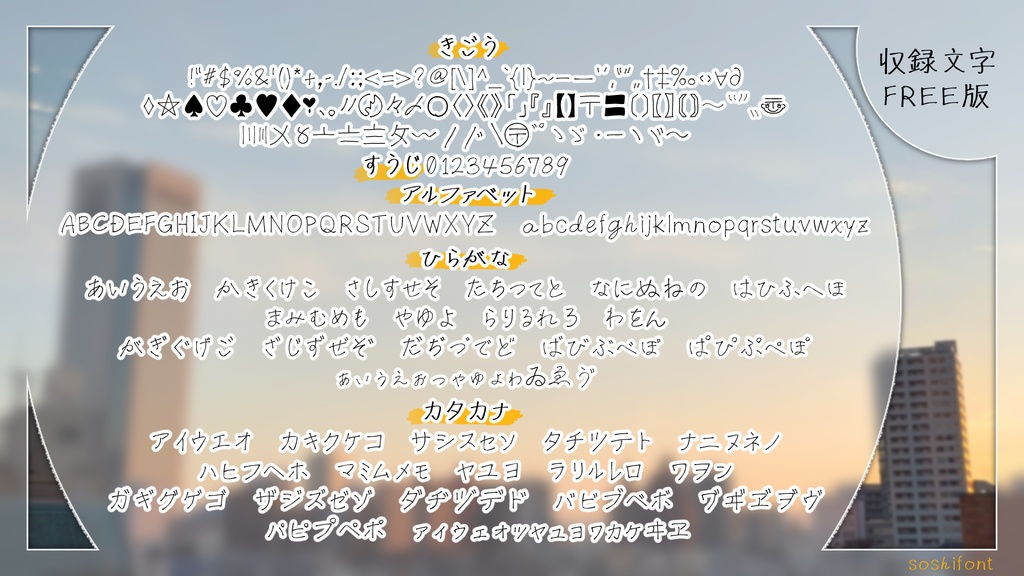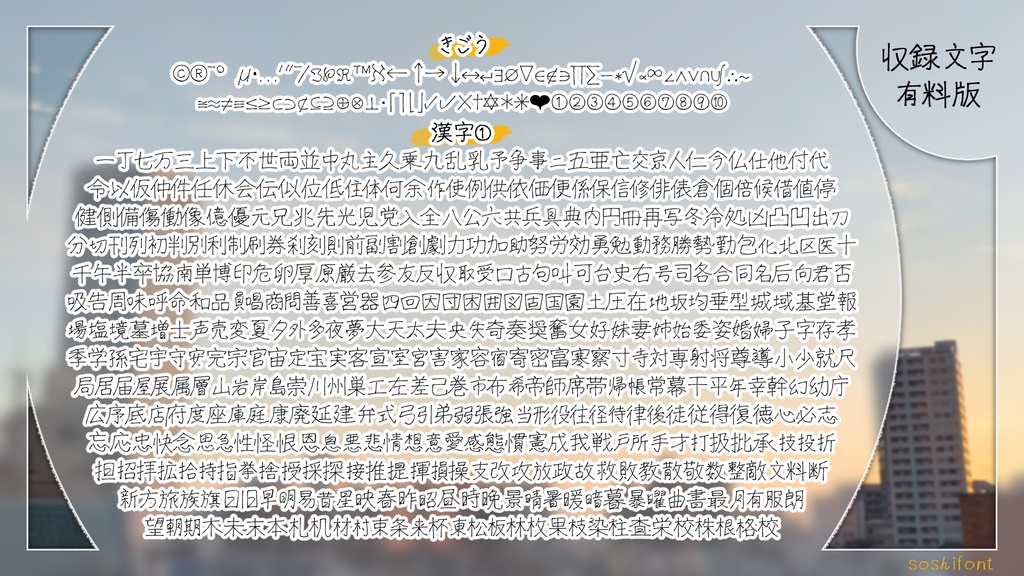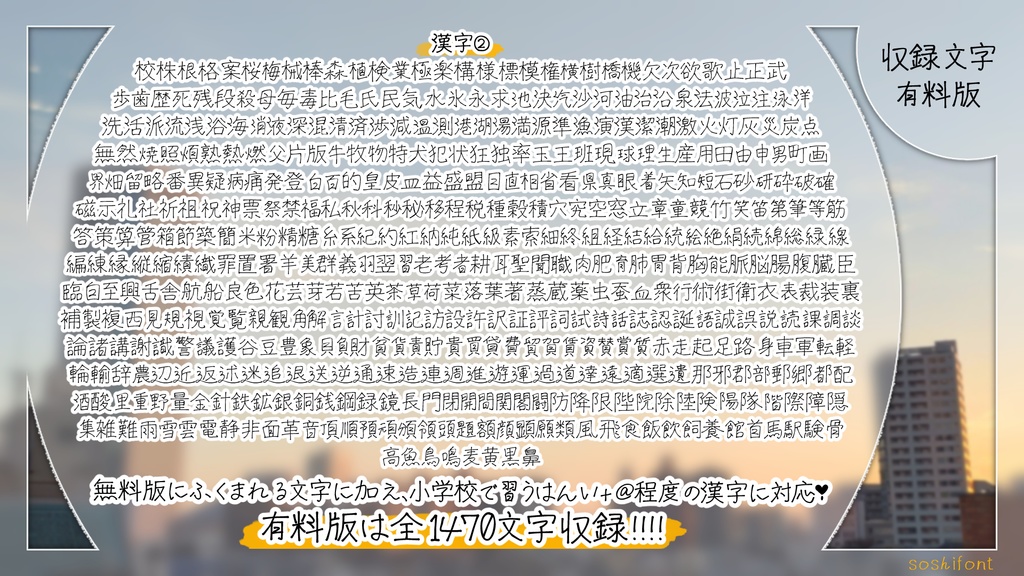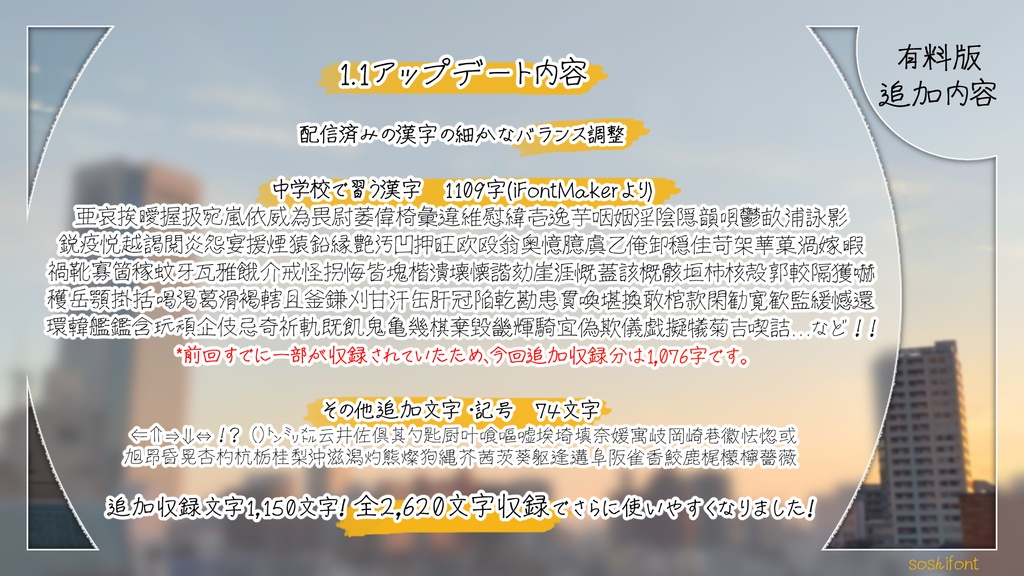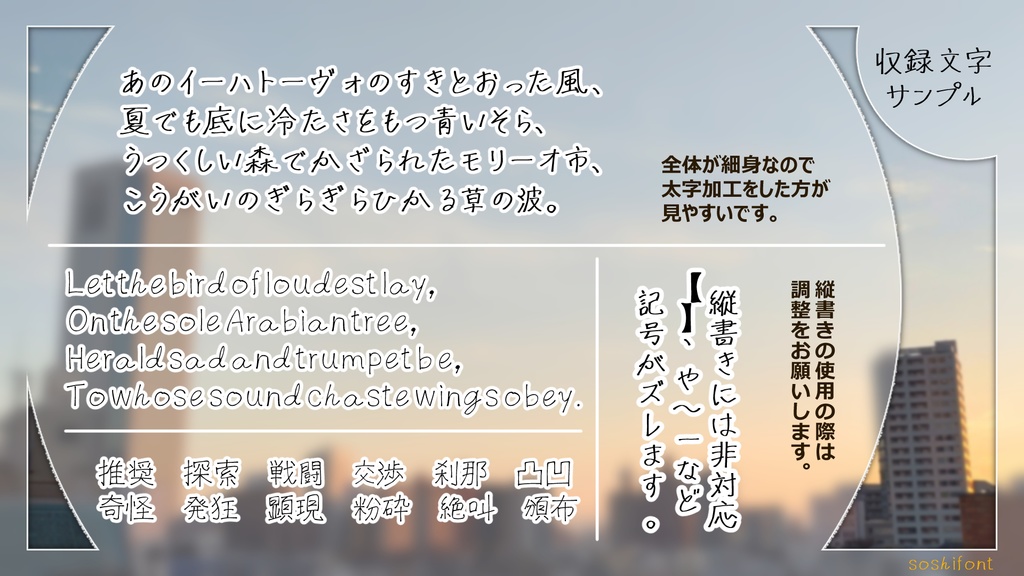
アプリiFontMakerで制作した手書きフォントです。 【フリー版】350文字収録 英数字、ひらがな、カタカナ、記号 【有料版】2700文字収録 フリー版の文字+漢字、記号 ▼25.2.15 追加文字リスト 仇伊匝卯叢咳哉唖喧嘩噂圭夷嬉宋尖屑恕悉惣 掻揃斯晋曾朔杖栗梓椙楚槍汐汲浩淳渚漕潅澗 灸狐獅玖瓜疏痔皐矩碓碩稀竿笠篠粟糟糠綜綺 聡舛苅荻菅蒼薗蘇蝉蹟醤鈎鎗閏阿雛雫駈鯖鼠 【有料版一覧PDF】 有料版に含まれる文字を確認できるPDFです。 ご購入時の参考にしてください。 ※有料版に同梱されている「収録文字一覧(PDF)」と同一の内容です。 【ファイル内容】 ・TrueType形式データ ・OpenType形式データ ・Readme ・収録文字一覧(PDF) 【利用に関して】 ▼商用•非商用での利用が可能です。 クレジット表記は任意です。 ▼禁止事項 •自作発言 •二次配布 •フォントを使用しての商標登録 •誹謗中傷目的、公序良俗に反する場面での使用 ▼著作権は放棄していません。 何かあればこちらまで Twitter:@ss_noonly Googlefoam:https://forms.gle/x98KupCfeCZVd5xt5 2023.03.25 頒布開始 2023.07.17 ver1.1アップデート版配信 2025.02.15 ver1.2アップデート版配信 2025.02.16 有料版文字一覧配信※文字確認用